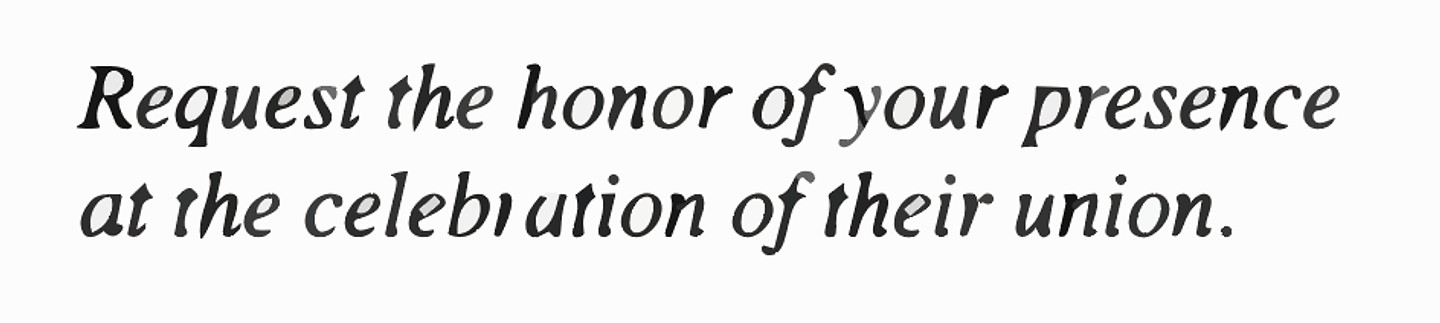
98% / 170,000 숫자 폰트가 궁금합니다! 한글 폰트는 산돌 고딕 네오길래 같은 폰트인가 했더니 다르네요 (ㅠㅠ)
제발 도와주세요ㅠㅠ ㅠㅠ 꼭 이게 아니더라도 비슷한 느낌의 폰트나 단어가 있을까요....? 손글씨라기엔 요즘 외국에서 사용하는 폰트같은게 다른 가게에서도 비슥한 폰트를 보았어서요 ㅜㅠ